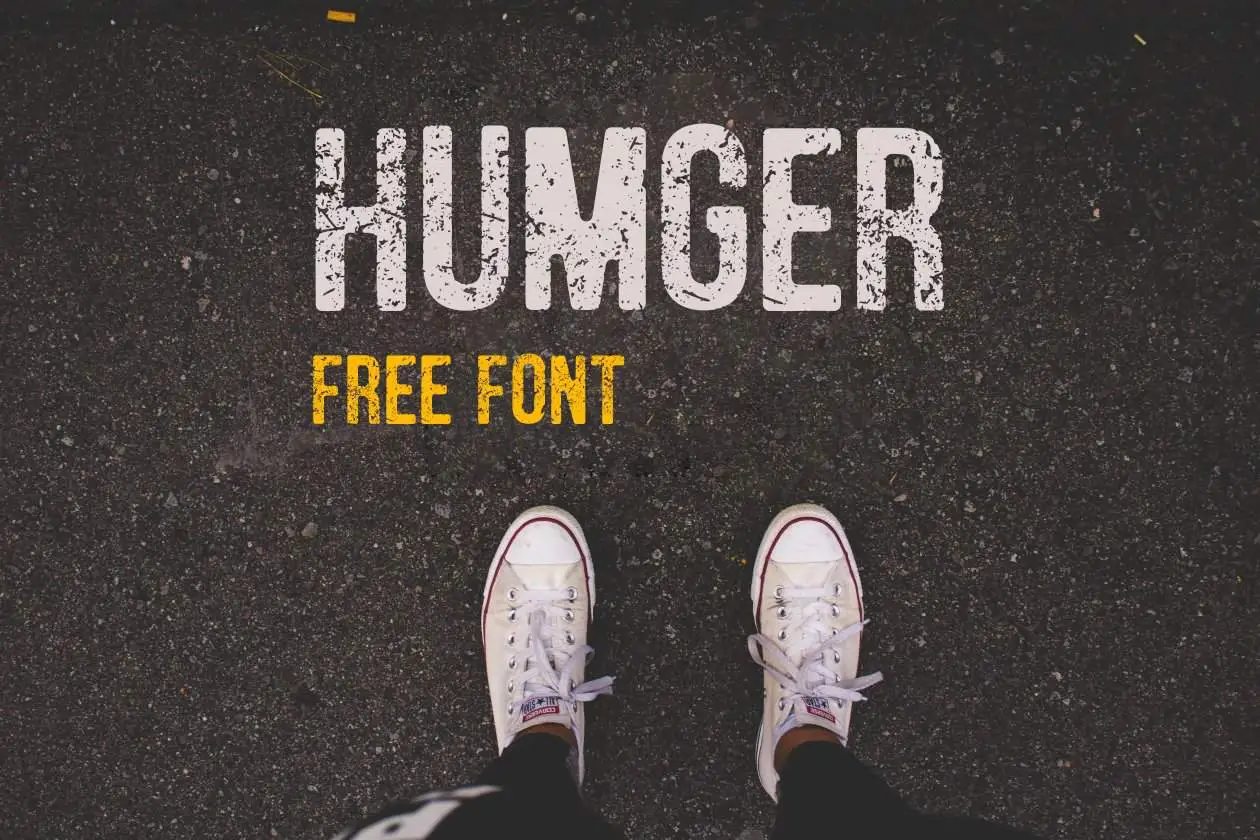
Humger Font – Fonte Grátis
Humger Font
Descubra uma nova opção para seu próximo projeto gráfico com a Humger Font. Desenhada pela graphicpear, esta novidade é um tipo de texto moderno e antigo que combina grau vintage com textura natural. A Humger é perfeita tanto para projetos pessoais quanto comerciais, oferecendo uma abordagem única ao seu design. Este ‘sans serif’ da categoria Display vem desenhado para capturar a essência do grunge, criando um efeito visual interessante em sua próxima composição visual. Inspirada no uso de texturas naturais e na sensação vintage que brota dos anos 80, essa fonte oferece uma abordagem única para quem busca algo diferente na criação de seu próximo design. É a escolha perfeita para aqueles desejando um toque único e versátil no seu trabalho gráfico.